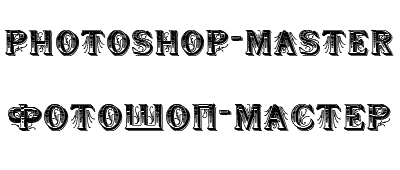
Отличный шрифт =)
спасибо, шикарный шрифт
Спасибо, такой веселенький получается текст :)
ПРИКОЛЬНО
симпотные, мерси.
Прикольно спасибо!!!
вау!!супер!!спасибо
Классный шрифт! Огрромное спасибо!
Отличный шрифт!
вау!!супер!!спасибо
Супер! Давно искала такие русские шрифты <З
Красивый шрифт. Только скачать не получается?
вау)
красивенько)
Очень красивый шрифт, спасибо!
ваще реальный !